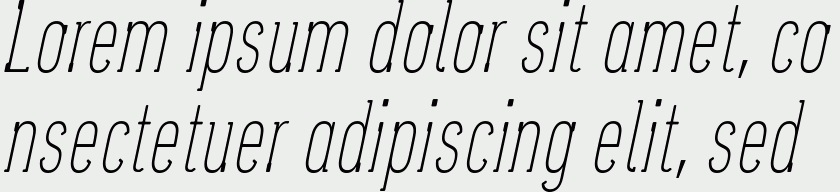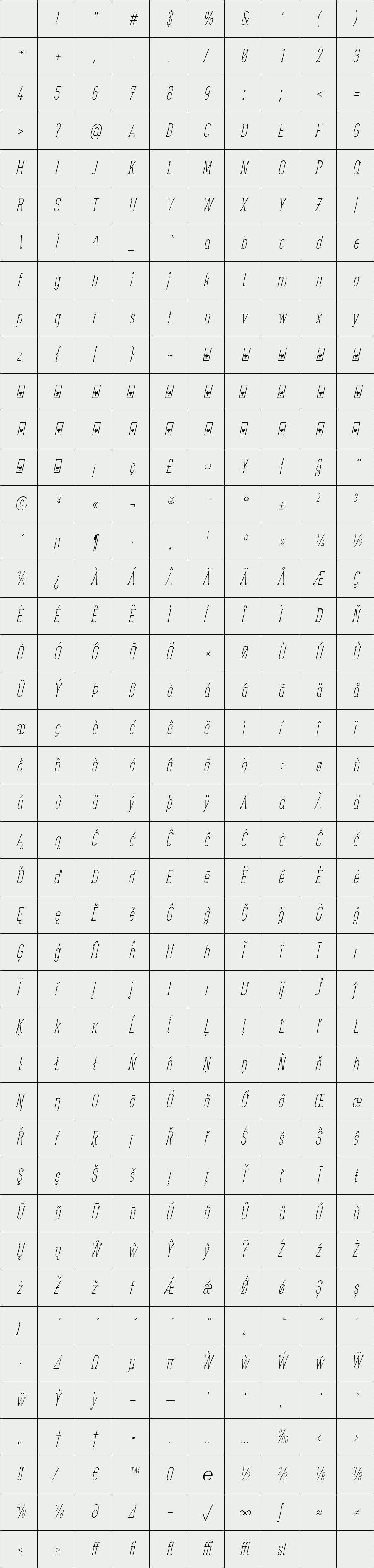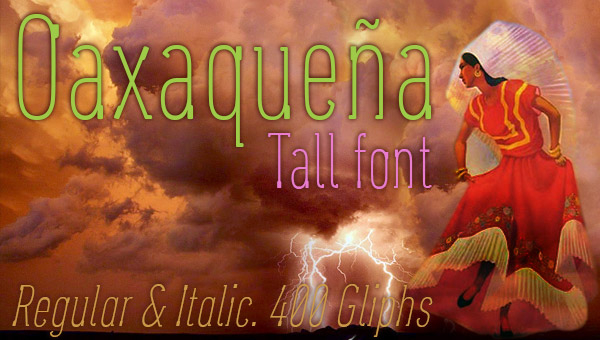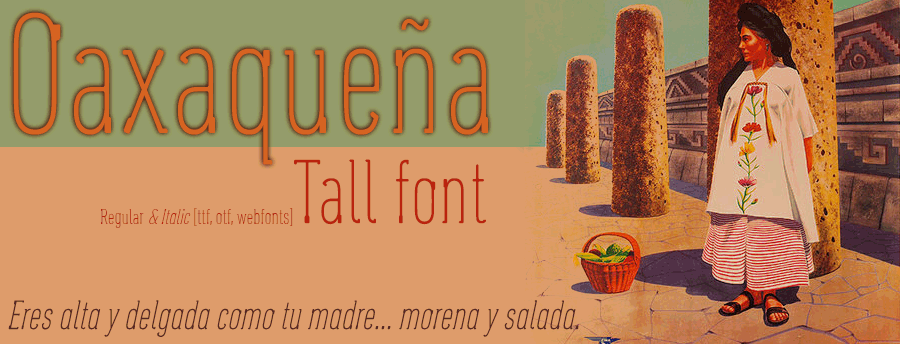
Oaxaqueña Tall
/ Oasaqueña Tall Italic
Es una tipografía extra fina y extra condensada, rematada con pequeños serif verticales de acabado redondeado.